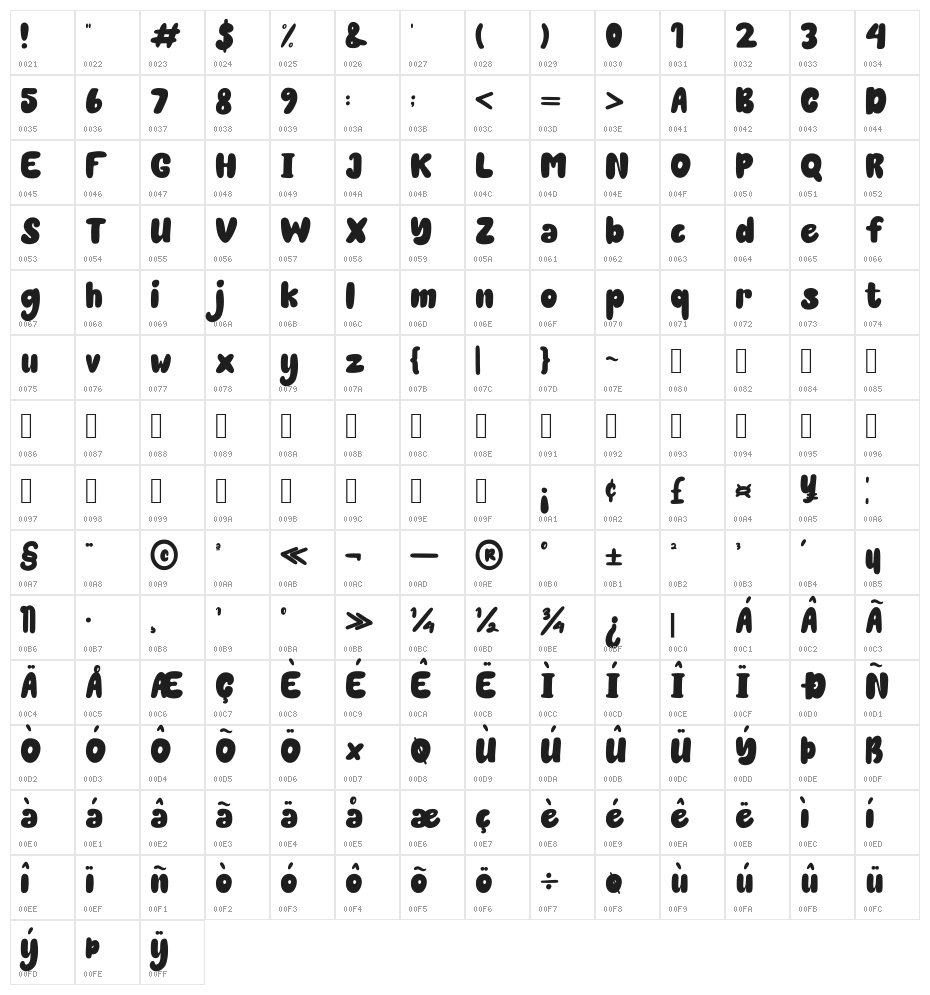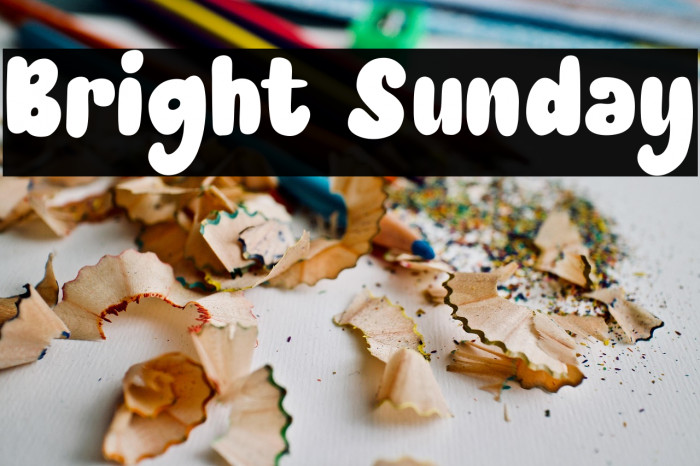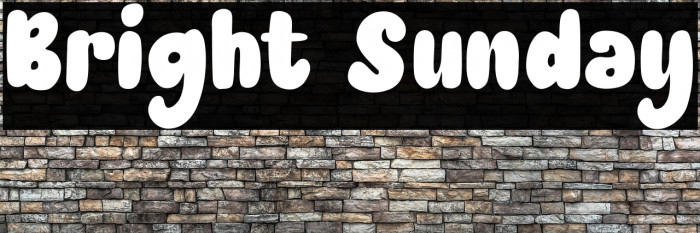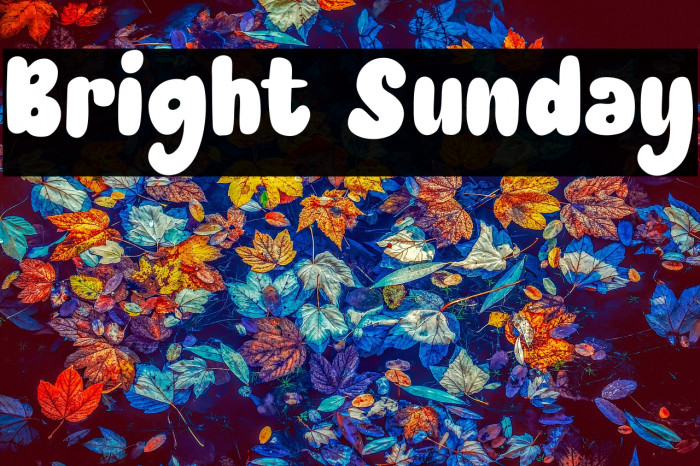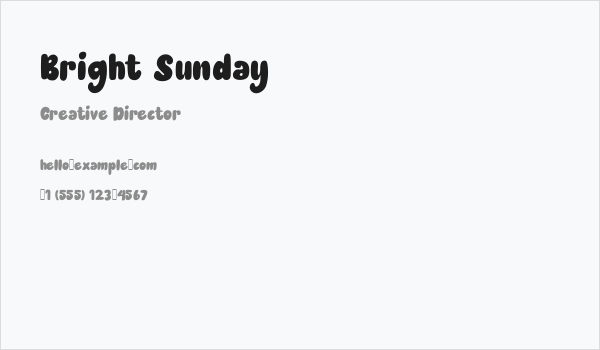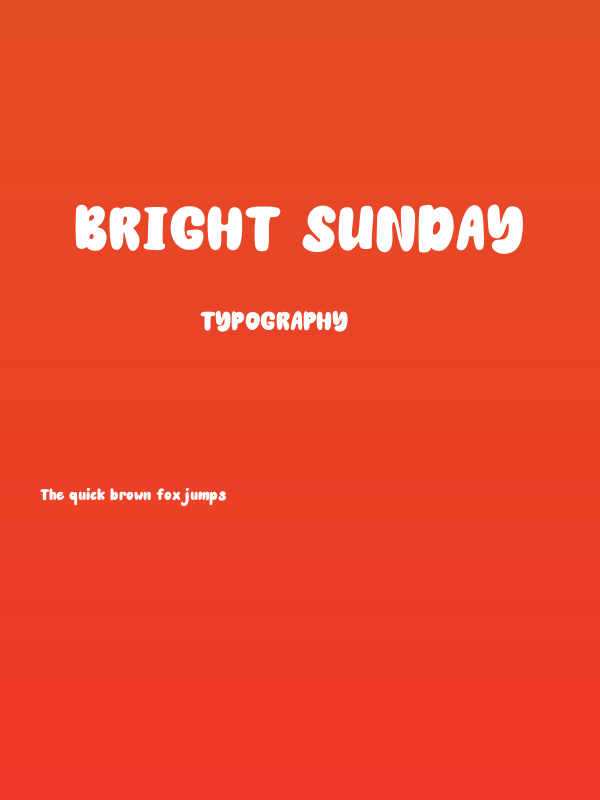
Bright Sunday Font
| Caso d'uso | Logos, Posters, Invitations |
| Progetti proposti | Ideal for children's books, playful branding, party invitations, and any design needing a fun and lively touch. |